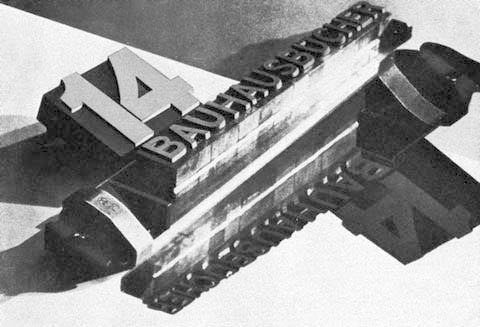
bauhausbuecher
A partir de 1923, e em estreita cooperação com
Walter Gropius, Moholy-Nagy concebeu e editou a série de
livros chamados bauhausbücher.
Deste modo, Moholy-Nagy foi o impulsionador das actividades
editoriais e publicistas da Bauhaus.
Ainda na Hungria, Moholy-Nagy participou na revista Ma
(«Hoje») , para a qual fez as capas; na Bauhaus, concebeu
vários números dos bauhausbücher (livros da
Bauhaus); fez também design de publicidade.
Nos seus manifestos, o conceito de uma nova tipografia
ocupava um papel central.
«die neue typographie» foi o título
programático de um artigo de Moholy-Nagy, publicado em 1923 no
bauhausbuch, foi um artigo que articulou ideias essenciais; pouco
depois, Jan Tschichold faz
ressonância às teses de Moholy-Nagy, ampliando a sua
divulgação.
Livro Painting Photography Film, desenhado por
Moholy-Nagy em 1927. |
bauhausbücher 5
Piet Mondrian: Neue Gestaltung László
Moholy-Nagy , 1924 |
bauhausbücher 14
Moholy-Nagy, L. Von Material zu Architektur.
München, Albert Langen 1929. 243 Seiten mit 209 Abbildungen.
23,5 x 18,5 cm. Orig.-Broschur mit Orig.-Schutzumschlag.
Bauhausbücher, Band 14 |
Catálogo, 1925
Bauhausbücher 7
Gropius, Walter. Neue Arbeiten der Bauhauswerkstätten.
München, Albert Langen Verlag 1925. 116 Seiten (davon 8 Seiten Text)
mit 107 Tafeln und 4 Farbtafeln. 23,5 x 18,5 cm. Bauhausbücher, Band
7. Erste Ausgabe. Mit einem kurzen programmatischen Text von Walter
Gropius. (Grundsätze der Bauhausprodution). "Kein Institut, keine
Ausstellung, keine Messe konnte zwischen den beiden Weltkriegen ein
imposanteres Kompendium neuer Möbel und Objekte des Alltags vorstellen als
dieses 'Bauhausbuch'." Heinz Spielmann. |
| Gleizes, Albert. KUBISMUS. München, A.
Langen, 1928. 1st edition. Cloth, Large 8vo, 101 pages. Heavily illustrated. 23
cm. In German. Bauhausbücher Nr. 13. . Includes 47 full-page
illustrations, and 2 pages of publisher's ads. First German edition of Gleizes'
"Cubisme" (Gent 1918), translated by Eulin Grohmann. Typography and design are
by L. Moholy-Nagy. |
Capa de livro, sobre o Cubismo, de Moholy-Nagy
1928 |